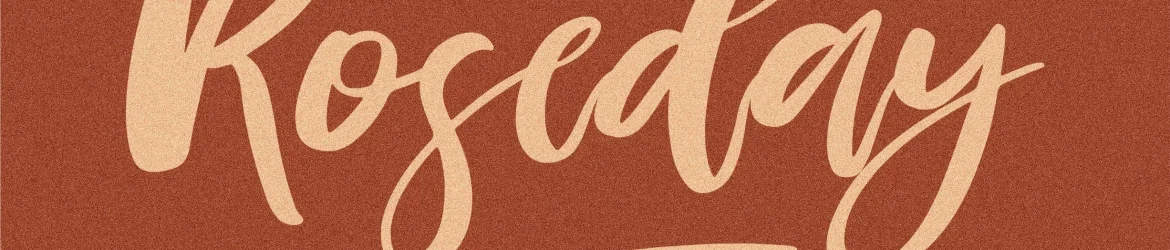
Roseday Font – Download Grátis
A Roseday Font é uma elegante fonte escrita à mão que oferece um toque único para qualquer projeto visual. Esta fonte foi criada especificamente para aquelas empresas e designers buscando incorporar elementos pessoais, autênticos e únicos em seus trabalhos. Perfeita para logos, projetos de marca, design de embalagens, mugs, cartões personalizados, capas de livros, etiquetas e até mesmo fotografias, a Roseday Font é um excelente complemento que pode transformar seu trabalho no topo da moda. Não importa se você está trabalhando em uma camiseta para uma festa especial ou em uma identidade visual de uma startup inovadora; a Roseday Font tem o poder de criar aquele toque único e autêntico que torna suas criações ainda mais memoráveis. Seja qual for seu projeto, a Roseday Font está aqui para trazer um ar de personalização à sua próxima ideia.